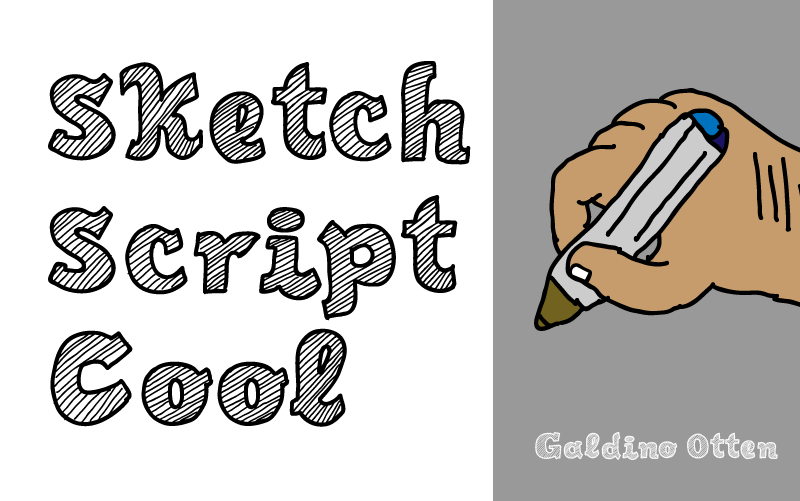
Sketch Script Cool Font – Fonte Grátis
Sketch Script Cool Font
A fonte Sketch Script Cool Font é uma escolha perfeita para quem busca um estilo elegante e sofisticado para projetos de design visual. Ideal para criar headlines memoráveis ou texturas decorativas, essa font apresenta traços suaves e fluidos que ajudam a destacar qualquer projeto. Desenvolvida pelo designer Hamilton, Sketch Script Cool Font oferece uma variedade de opções para personalização, desde as nuances delicadas das letras até os detalhes dramáticos dos traçados. Perfeita tanto para uso em redes sociais quanto para criação de identidades visuais complexas e arrojadas, esta font pode transformar qualquer projeto em um verdadeiro trabalho de arte. Se você está procurando por uma opção que combine elegância com versatilidade, Sketch Script Cool Font é uma excelente escolha.